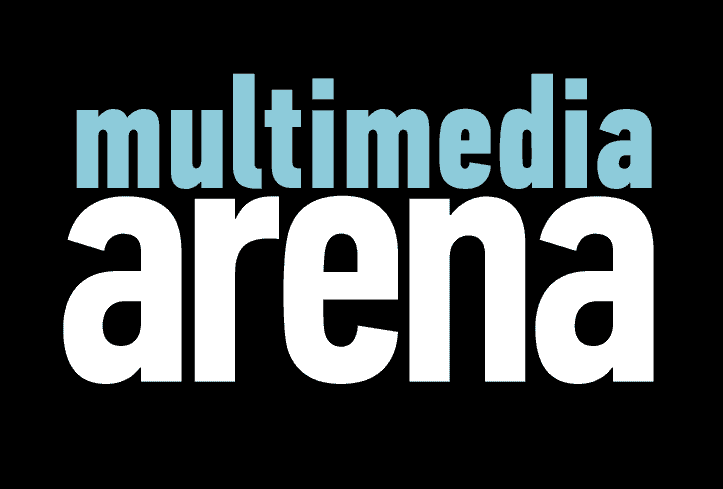
A família Din Text Compressed Pro é uma escolha excepcional para projetos que exigem alta qualidade de legibilidade e simplicidade ao mesmo tempo. Ela foi criada com um objetivo específico: proporcionar os melhores resultados para tipos de texto, sem comprometer a elegância ou o estilo mais sofisticado. O grande destaque do Din Text Pro é sua série de pesos diferentes, cada um composto por uma média de 1280 caracteres. O que diferencia este projeto da maioria dos outros sistemas de fontes é o fato de suas linhas minúsculas não serem superpostas nas alturas das letras maiúsculas e as itálicas não são uma versão mecânica-obliqua das pesos normais, mas sim verdadeiras itálicas. Isso permite que a família mantenha um equilíbrio perfeito entre força e elegância. Esta fonte é ideal para projetos profissionais que exigem grande precisão de texto sem comprometer o design gráfico mais sofisticado. Ela se destaca por sua versatilidade, oferecendo uma solução completa para a necessidade de textos legíveis em diferentes contextos, seja eletrônico ou impresso. A Din Text Compressed Pro é uma escolha inteligente para qualquer projeto que valoriza tanto a elegância quanto o conforto do olho.